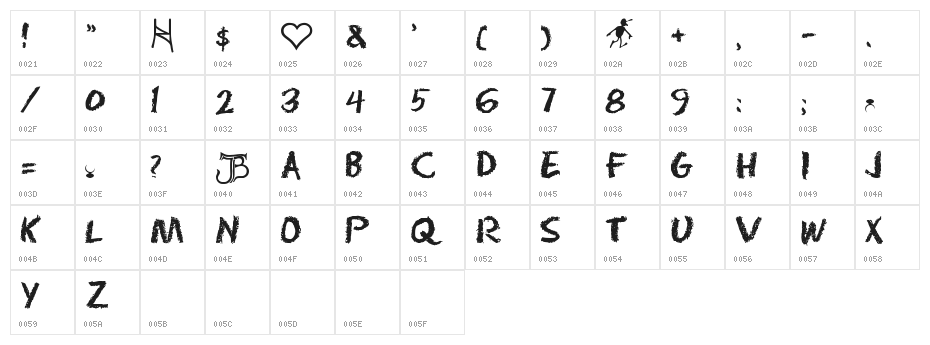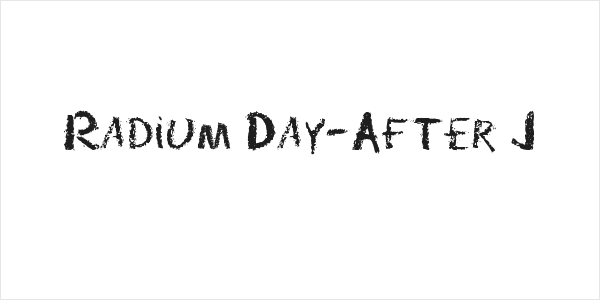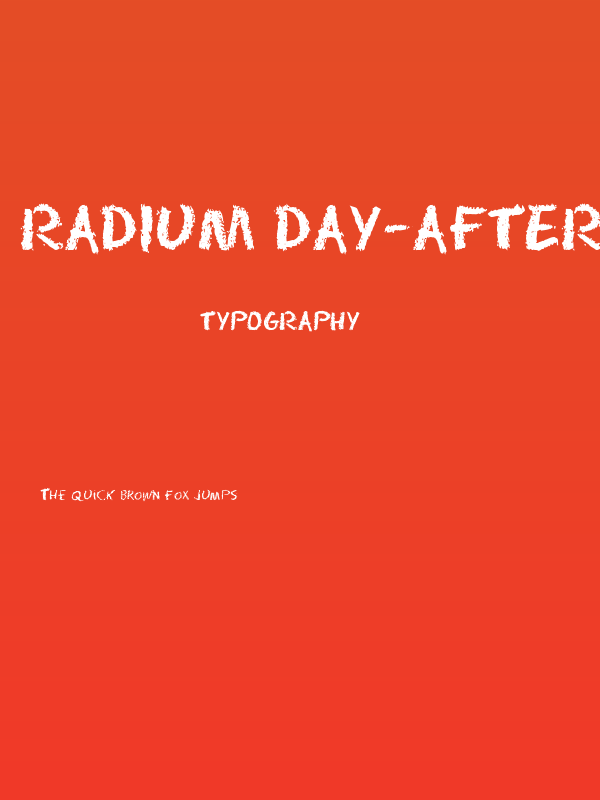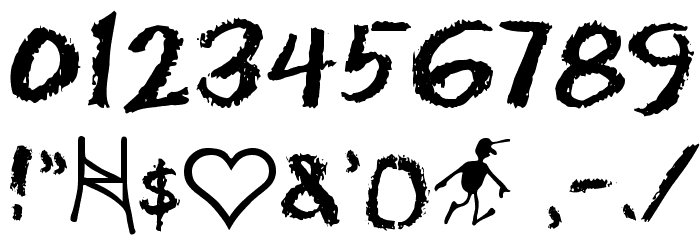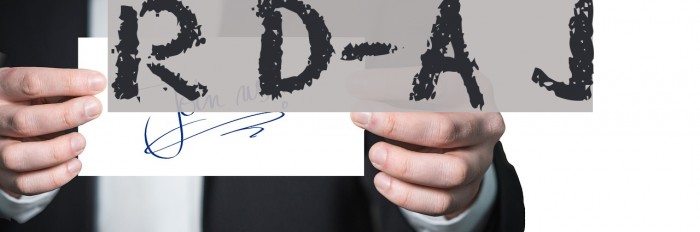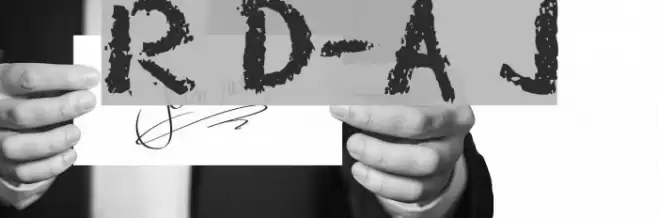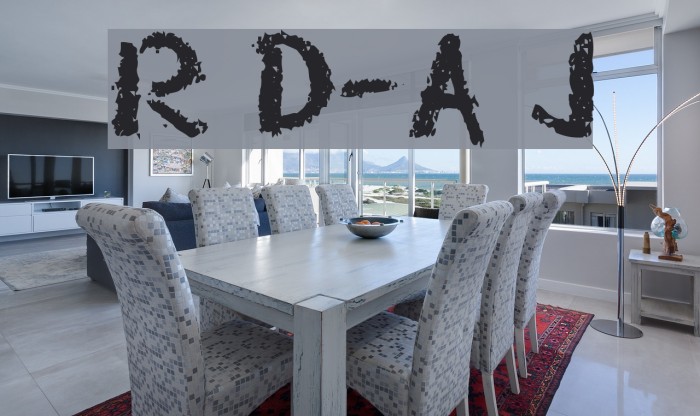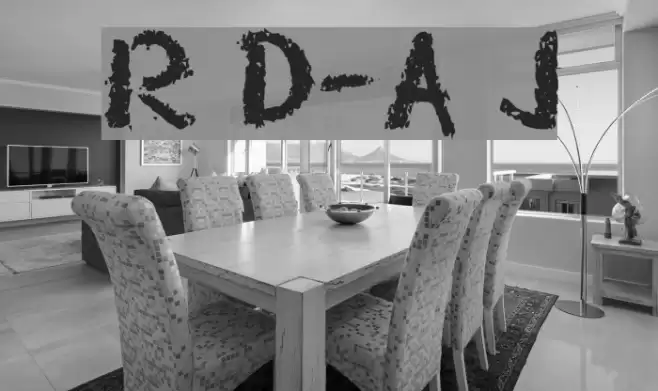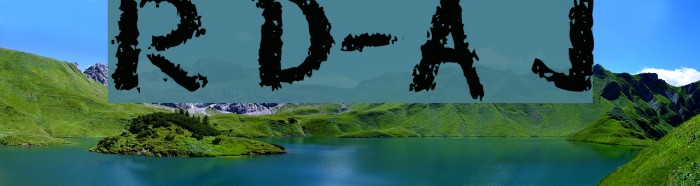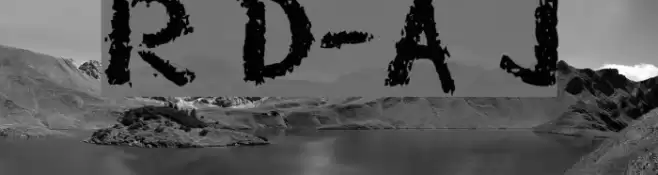
Radium Day-After J Font
| Nom | Radium Day-After J |
| Poids | Perished |
| Version | Version 'Advantage Becker' july 29 1995 |
| Cas d'utilisation | Headlines, Logos, Artistic projects |
| Projets proposés | Ideal for posters, album covers, graffiti art, and branding that requires a bold, artistic touch. |